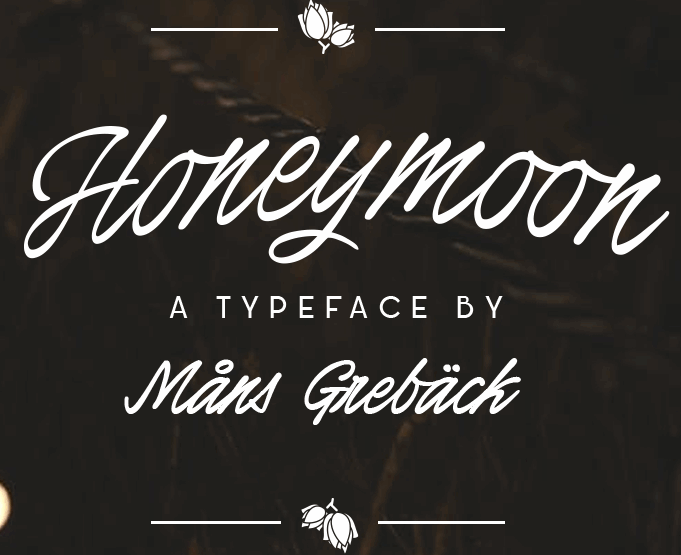
A Honeymoon Font é uma elegante foice escrita a mão criada pelo designer sueco Måns Grebäck. Seu design delicado e harmonioso cria linhas finas e suaves que prometem dar ao seu projeto um toque refinado e personalizado. Embora seja uma fonte de estilo a mão, mantém uma estilização cuidadosa que não é excessivamente onipresente ou intrusiva. Ideal para uso em letras do título ou pequenas seções destacadas, a Honeymoon Font adicionará um toque sofisticado e único ao seu design. Como designer de fones profissional, Måns oferece suporte atencioso e frequentemente atualiza sua coleção com novas fones de qualidade para seus amantes. Visite o site do designer em www.mansgreback.com ou siga ele no Facebook através da página de Facebook: http://www.facebook.com/mansgreback. Não deixe de dar uma olhada nas outras maravilhas gráficas que Måns criou e compartilhou com a comunidade de fones online.